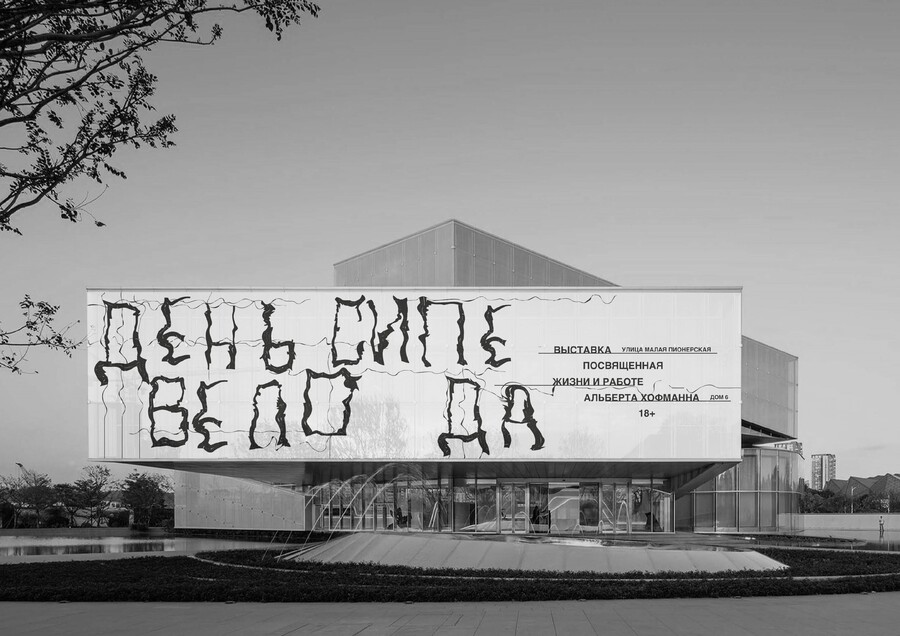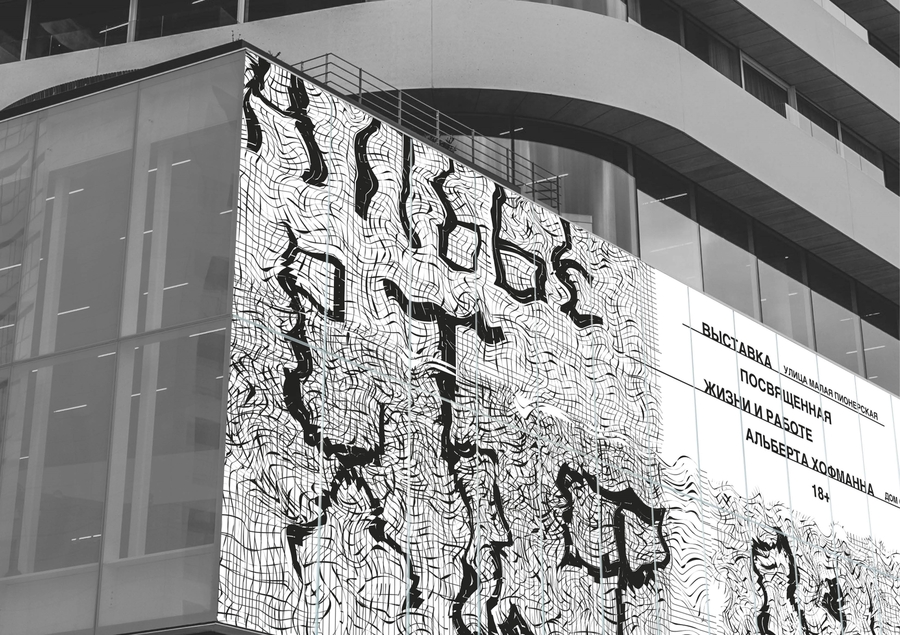
LSD font — акцидентный шрифт для выставки ученого Альберта Хофманна, химика, который синтезировал ЛСД. В шрифте и айдентике я постаралась передать эффект этого вещества — хаотичность, непостоянность, искажение пространства. Черно-белое оформление выставки сделано с целью гармоничного расположения ярких экспонатов и сохранения научного характера выставки.